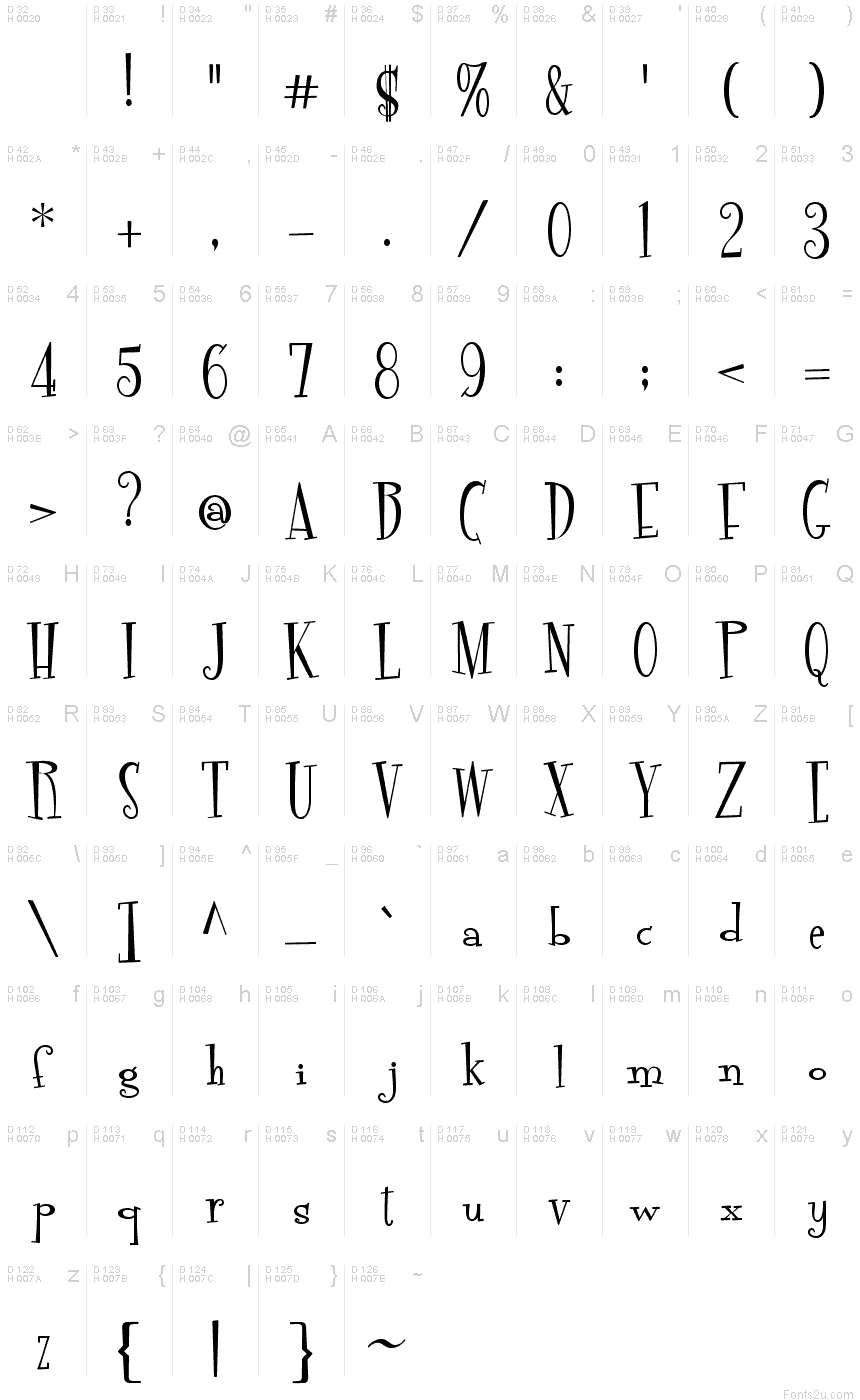
Fontdinerdotcom od Font Diner je bezplatné komiksové písmo typu display s uvolněným, ručně psaným stylem, který působí jako vystřižený z titulků kreslených filmů z poloviny minulého století. Jeho vysoké, tenké tahy a měkké, kulaté tvary dodávají slovům roztěkaný, neotřelý rytmus – jako by někdo rychle načrtl inkoustem nápis na výlohu bistra. Díky nepravidelným rozestupům a hravému náklonu působí text energicky a spontánně, rozhodně ne strnule nebo mechanicky.
S Fontdinerdotcom získají nadpisy okamžitě retro, lehce bláznivý šarm, který se skvěle hodí na obálky dětských knížek, komiksové panely, jídelní lístky v kavárnách, narozeninové pozvánky, retro loga nebo náhledy videí na YouTube. Toto bezplatné písmo nejlépe vynikne ve větších velikostech, kde jeho protáhlé tvary a svérázné proporce mohou dýchat; pro hlavní text jej kombinujte s čistým bezpatkovým písmem, abyste zachovali čitelnost a vyváženost sazby.